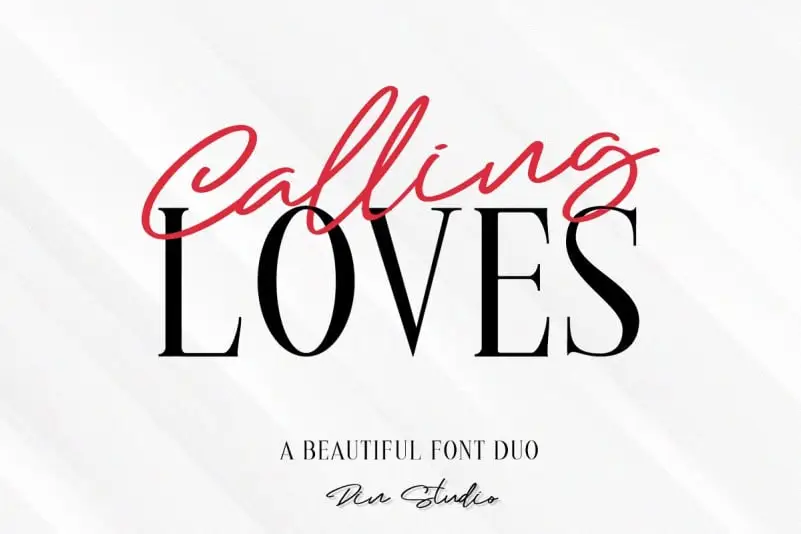
Calling Loves Font Duo – Download Grátis
A Calling Loves Font Duo é uma combinação arrebatadora de uma tipografia script seca escrita a mão com uma serif bold que possui curvas suaves em todos os cantos, projetada e compartilhada pelo Din Studio. Esta fonte perfeita para suas necessidades de design. Introduzimos agora Calling Loves. Esse é um duo de fontes lindas, projetado sob um estilo moderno. A combinação da tipografia script com o elegante serif vai fazer seu trabalho de design mais belo e atraente. Perfeita para marcações, designs web, assinaturas pessoais (logos) e muitos outros tipos de designs modernos. Uma fonte que faz do seu trabalho um projeto ainda mais especial.